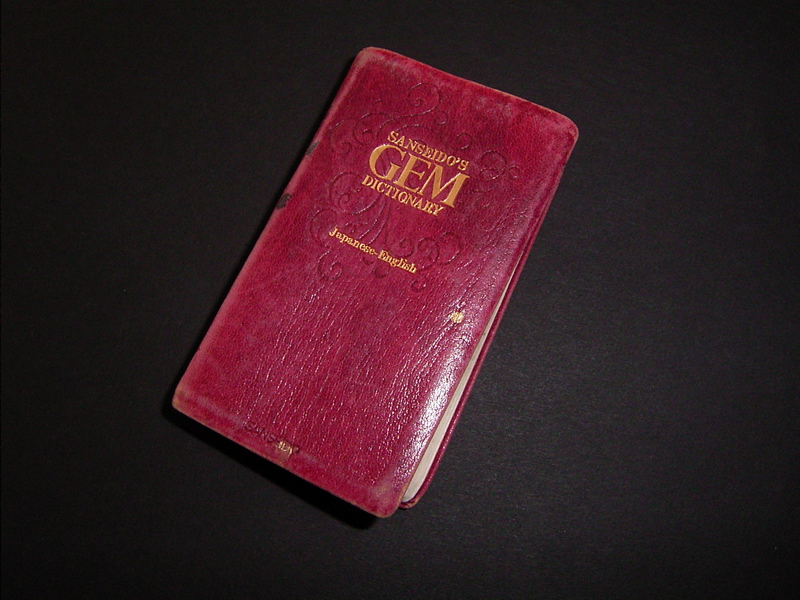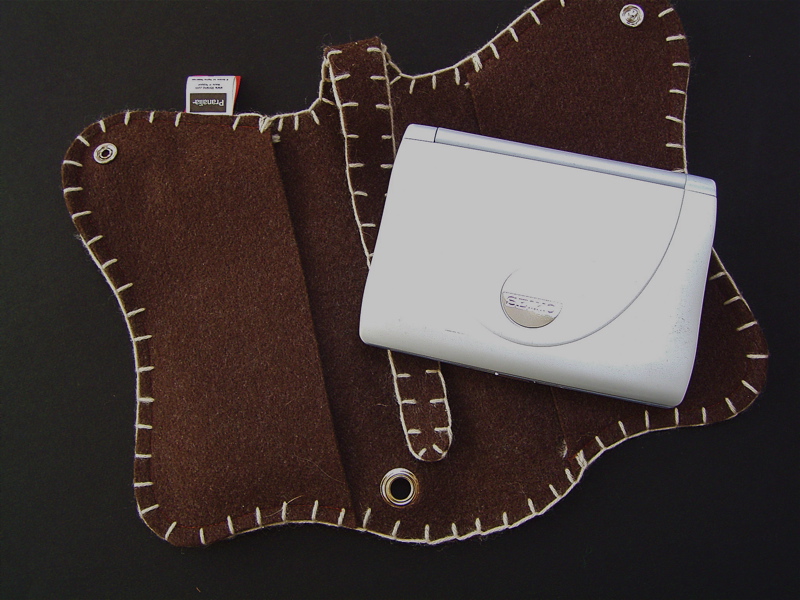
辞書
カリグラフィーでは、英語の文章を書く事が多いので、辞書は必需品です。
昔は三省堂のGEMがいつも側にあって、海外ワークショップの時には必ず旅のお供でした。
1996年にアメリカのシアトルで行われたコンファレンスの事です。初日教室に集まってみたら、同じクラスに偶然3名の日本人が参加していることがわかりました。一人ずつ英語で自己紹介をして行った時、まず最初の日本人が「私はこれ(三省堂のGEM)持って参加しています」と言うと、次の人も「私もこれを持って来ました」と言って同じGEMを披露。そして最後に私も「実は私も持ってます・・・・」とGEMを掲げました。
全く同じ辞書を3人とも持参していたのです。おおお、GEM大人気!
だって、小さいのに、英和、和英どちらも載っているニクイ奴なのです。本当にお世話になりました。
しかし、今は電子辞書に取って代わられ、GEMを持ち歩く事はもうあまりなくなりました。機能が一杯付いている、ってことも確かにその理由ですが、何と言っても、GEMの文字はもう小さすぎてよく見えません、悲し〜!
でも、もしかすると今に電子辞書の文字も見えづらくなってきて、おばあさんの様に虫眼鏡で見る様になるのかも・・・・。はぁ〜・・・。
そしたら、虫眼鏡ケースも探せばいいか!
お気に入りの定規
カリグラフィーは線のアートでもあるし、何より線を引いてから文字を書く事が大変多いので、定規は毎日の作業に欠かせません。
この大小の三角定規には、取手が付いています。高価な定規ほど平らなので、机の上にぴたっと乗っていると取りにくいのですが、これはそんな心配はありません。
スイスイとすぐに持てるし、たてよこ角度を変える事も簡単です。日本では見た事がありませんでしたが、ドイツに行った時に文房具屋さんで買いました。ひと つはFarber-Castell、もうひとつはSTAEDLERです。どちらもMade in Germanyでした。ドイツ製の文具というだけで、とても実用性がありそう・・・!
平行線を引くにはT定規が便利ですが、なぜか日本には小さくて扱いやすいものがありません。
水色のT定規は30cmなので、ちょっと使うのにとても便利。プラスチック製で軽いし、持ち運びも便利。イギリス製でHELIX社のものです。日本の文具はデザインも実用性にも優れたものが多いのに、なぜ小さなT定規がないのか不思議です。
さてさて、私の最もお気に入りの定規は、この緑のもの。20cmでFarber-Castell製です。もちろんこれもMade in Germany。これは文房具が大好きだった父の形見ということもありますが、その計りやすさがダントツに素晴らしいからです。一度使ってみるとわかります。たぶん、ロングセラーだと思うので、大きな文房具屋さんなら必ずあるでしょう。
父は日本橋の丸善で買って来て、長く使っていました。今でも同じ物は買えるけど、なくしたら困るので、どうしてもこれは門外不出。家でしか使わない定規なのでした。
オリンピックロゴのお話し
昨日の早朝はみんなが荒川さんの金メダルに沸いて、幸せな気分をもらいましたね!!早起きは三文の得というよりいったいどれだけの得を頂いたことでしょうか〜。良かった、良かった!
さて、会場のあちらこちらに「passion lives here」という筆文字のようなロゴ?カリ?を目にしますが、誰の手によるものなのでしょうか・・・知りたい、知りたいとインターネットを調べてみましたが、オリンピックのロゴ自体はBenincasa-Husmann studioがデザインしたとトリノ五輪の公式HPには説明がありました。
大会中に使用するロゴというものは全部同じstudioがデザインするのでしょうか・・・。素人にはわかりません。どなたかご存知の方がいらしたら是非、是非教えて下さいね〜。
「passion lives here」という文字は素敵ですね。大会に夢中になりますが、大会に使われているロゴやデザインも一流のものなのでとても気になり、見ていて飽きません!
・・・さて、HPを探すときにgoogleにお世話になっていますが、みなさんはこのgoogleのタイトルロゴのイラストがよく変わっているのをご存知ですか?先月はモーツアルト生誕250年がらみのイラストでした。現在は・・・もちろんオリンピックのゲームに関するイラストです。それもいろんな競技で更新されています。googleタイトルをクリックすると過去のオリンピックゲームのイラストが出てきます。これを見るのも中々楽しいです。今日はアイスホッケーですね〜。個人的にはカーリングのストーンがgoogleのoの文字になぞらえられているデザインが気に入っています!意外なところで遊んでますね〜google!えっと何々?2006 Winter Games Doodle・・・って・・・なるほどねぇ〜。
パステル用のサンドペーパー
パステルに向いている紙はいろいろありますが、大体は線の入ったレイド紙か、地のテクスチャーが見える様なちょっとざらっとした紙です。
しかし、サンドペーパーに描くこともあるのです。
もちろん本当のサンドペーパではありません。れっきとしたパステル用の紙として売られています。
パステルなど画材で有名なフランスのセヌリエというメーカーから出ていて、色もけっこう沢山あります。何年か前に神保町のミューズのおじさん(社長さんか な?)に勧められて買ってみたのです。文字はざらざらしすぎてダメかな、と思ったら、以外や以外、パステルの粉が目地に入り込んで、結構表面は平らになる ので書けるのでした!
もちろん、定着させるためにフキサティフもかけています。
この紙の名前はよくわかりません。セヌリエのパステル用サンドペーパーでたぶんわかるでしょう。1枚650×500mmで¥1480です。かなりお高いざますわね。だっておスランス製ですもの・・・・・・。
ちょっと変わった紙に書いてみたい方、お試しあれ〜。
文字入りマット
ここのところ私の住んでいるあたりはぽかぽか陽気です。春らしい光が部屋に入ってくると本当にうれしい。
部屋の中はまだまだ冬バージョンなのですが。
インテリアといえば、床に敷く肌触りの気持ちいーいラグは大好きなのですが、玄関マットとかキッチンマットとかの類が実は苦手です。
ですが、今年の冬は寒かった!玄関床のあまりの冷たさと寒々しい雰囲気に負けました。
我が家を訪れてくださる方にも申し訳ないので、マットを購入しました。
高級品ではないけれど、とりあえず冷たさは回避。
アルファベットのOが並んでいるのを選んでみました。いや、数字のゼロ、またはただのマルかもしれませんが・・・。
私にとってはOなのよ、ということで。
このマットを見た家族からは不評でした。こんなところにまで文字、しつこいよ。だそうです。
えー、いいじゃないよー、文字があるのは楽しいよー。暖かくなるまではコレでいきます!
でも文字を踏むのはちょっとためらわれるのですよね。踏まないでマットの横から出入りしていたりして・・・何のために敷いてあるんだか?
しかもシッポのある家族が最近やってきたので、どうも狙われています。そこはトイレじゃないのよ!
diploma事情
さてさて、今月はdiploma(証書)のお仕事に追われていました。ドイツ語ではUrkunde(ウアクンデ)といいます。証書入れはMappe(マッペ)です。・・・ミニ知識でした。
ドイツ語関係の翻訳賞の授賞式に引き渡される証書は、全て手書きです。賞のシンボルである「羽」をイメージしたイラストが入るだけであとはシンプルなレイアウトで決まり。何度か試し書きをして、打ち合わせをして・・・これでいきまょう!ということで指定枚数を書き上げます。証書入れもB4サイズで入るものを手作りです。こういうものを作る紙やら素材やらを探すのも仕事の一つで、とにかく画材屋、紙屋を歩き回ります・・・。やせるかなぁ・・・?
今時は全て印刷されたものが多い中、手書きにこだわってくれるこのクライアントさんは貴重です。しかし、今でも手書きの証書を渡している現場もそこそこ存在しているのです。ロレアルアーツアンドサイエンスファンデーションも毎年ティニー三浦さんのカリと美しく装丁された証書を渡しています。